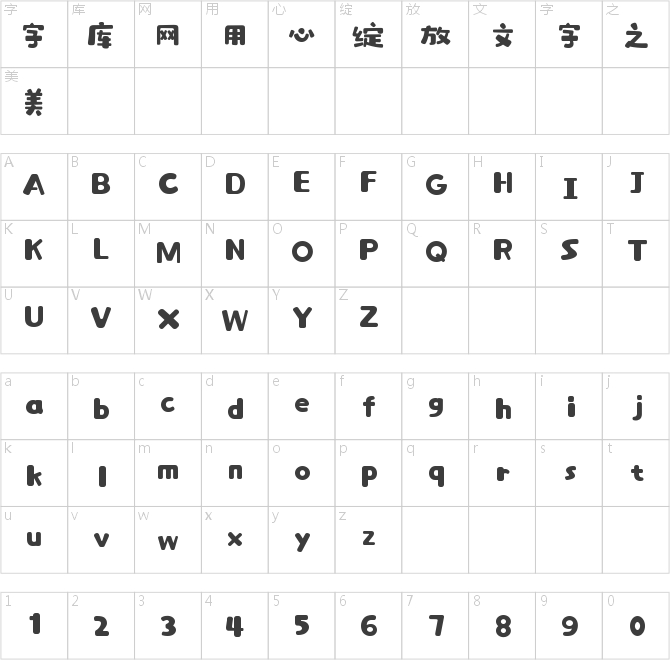
上首熊貓體,字體筆畫錯落有致;筆畫整體采用不規則處理,增加了字體整體的韻律。字體整體圓潤可愛、活潑感十足,適用于搭配標志、廣告標語、商業廣告、海報字體等高端屬性。
上首熊貓體字體字庫是一款讓人賞心悅目、百看不厭的中文字體,適合各類廣告和產品包裝設計應用,字體大小4.07MB,格式為ttf字體,上傳用戶是上首造字,作者/版權方為上首造字